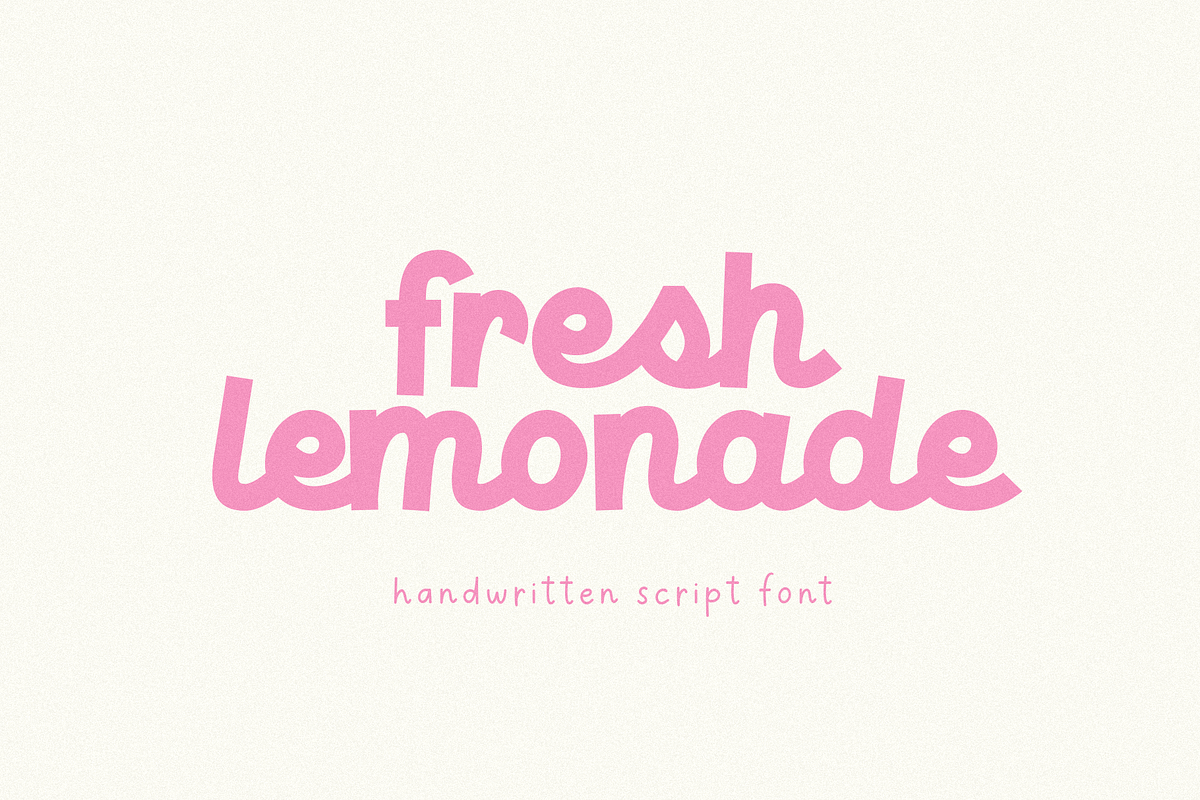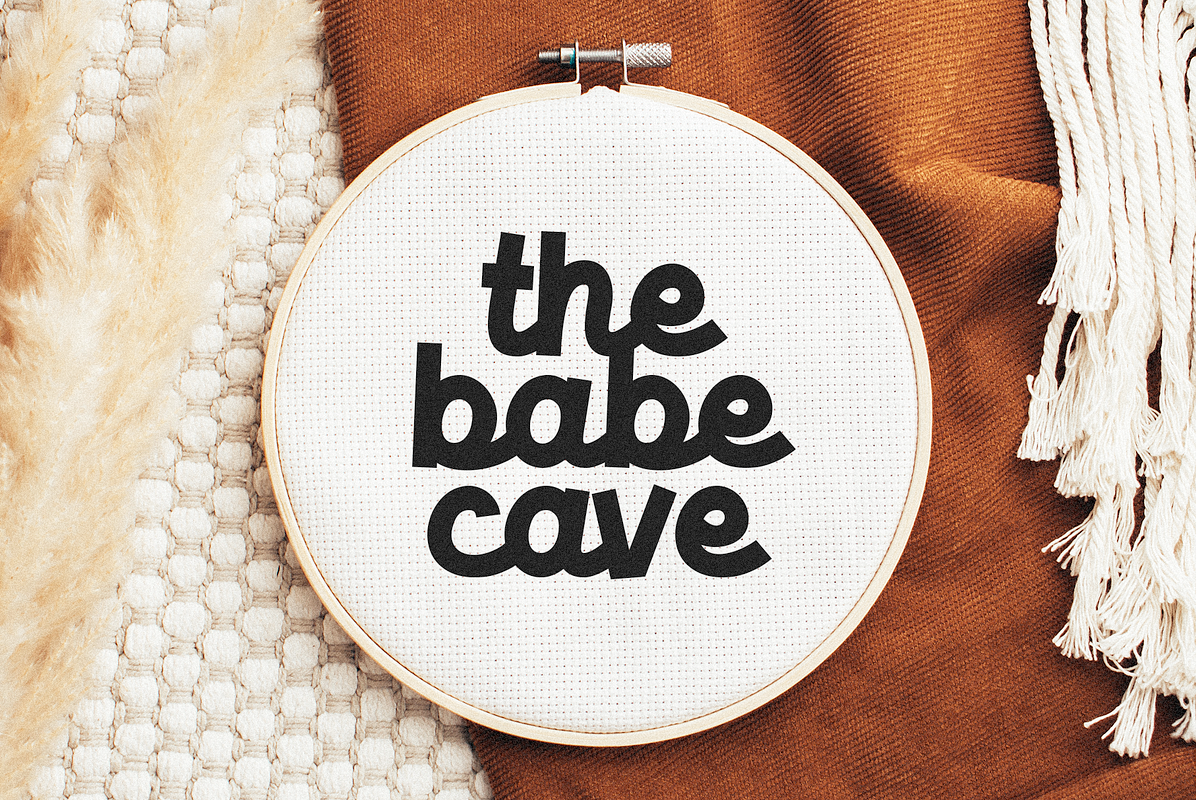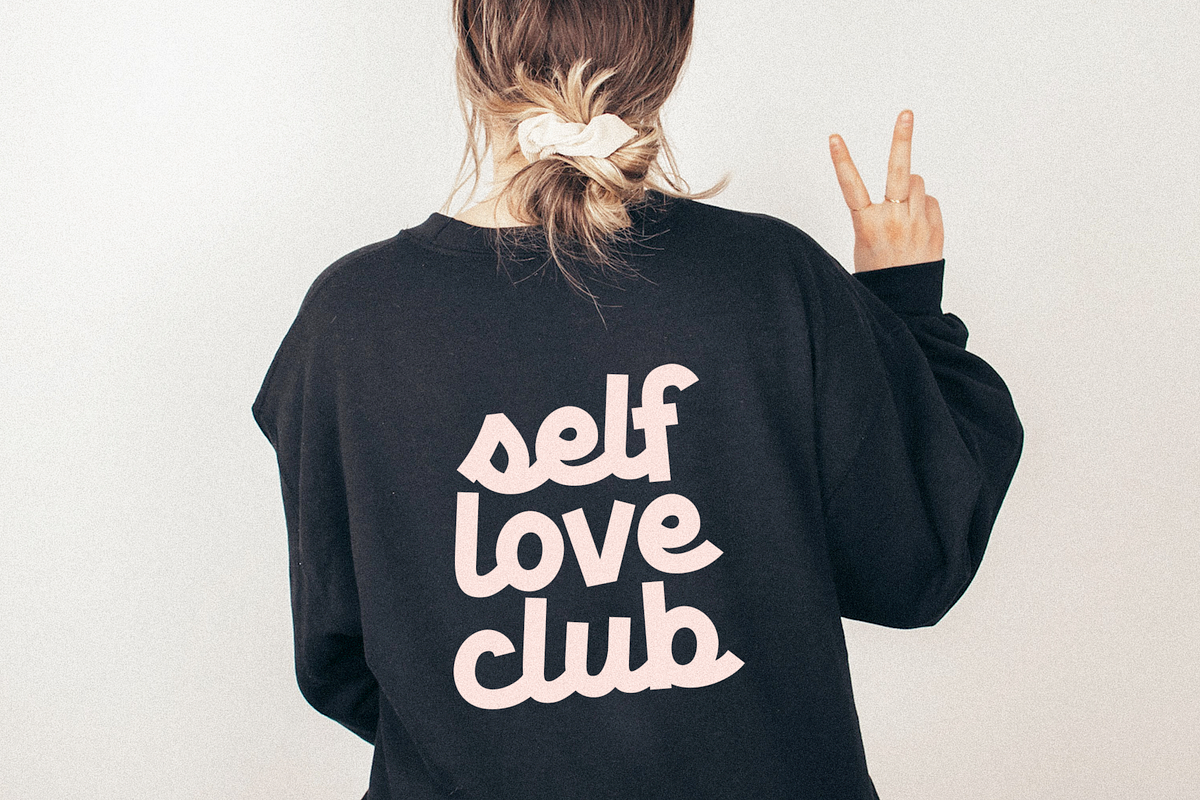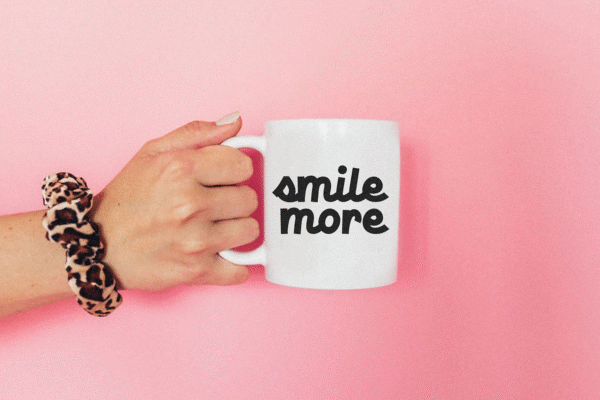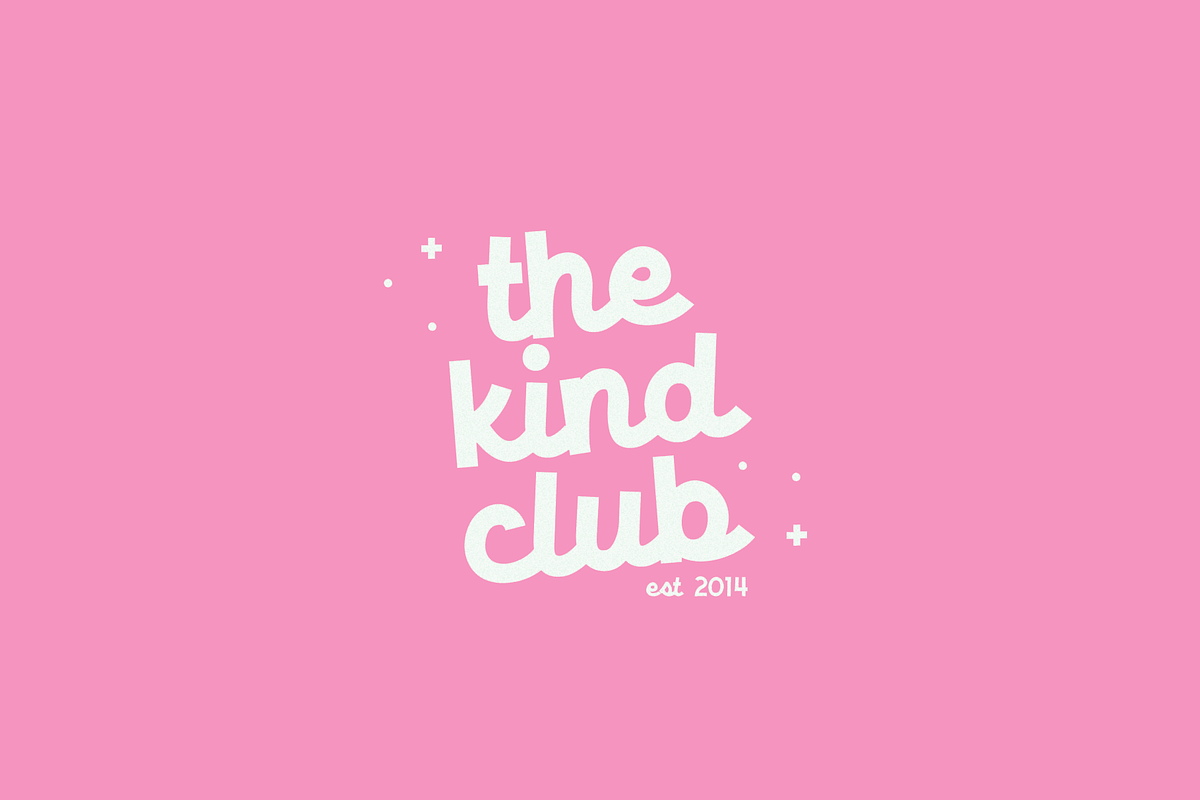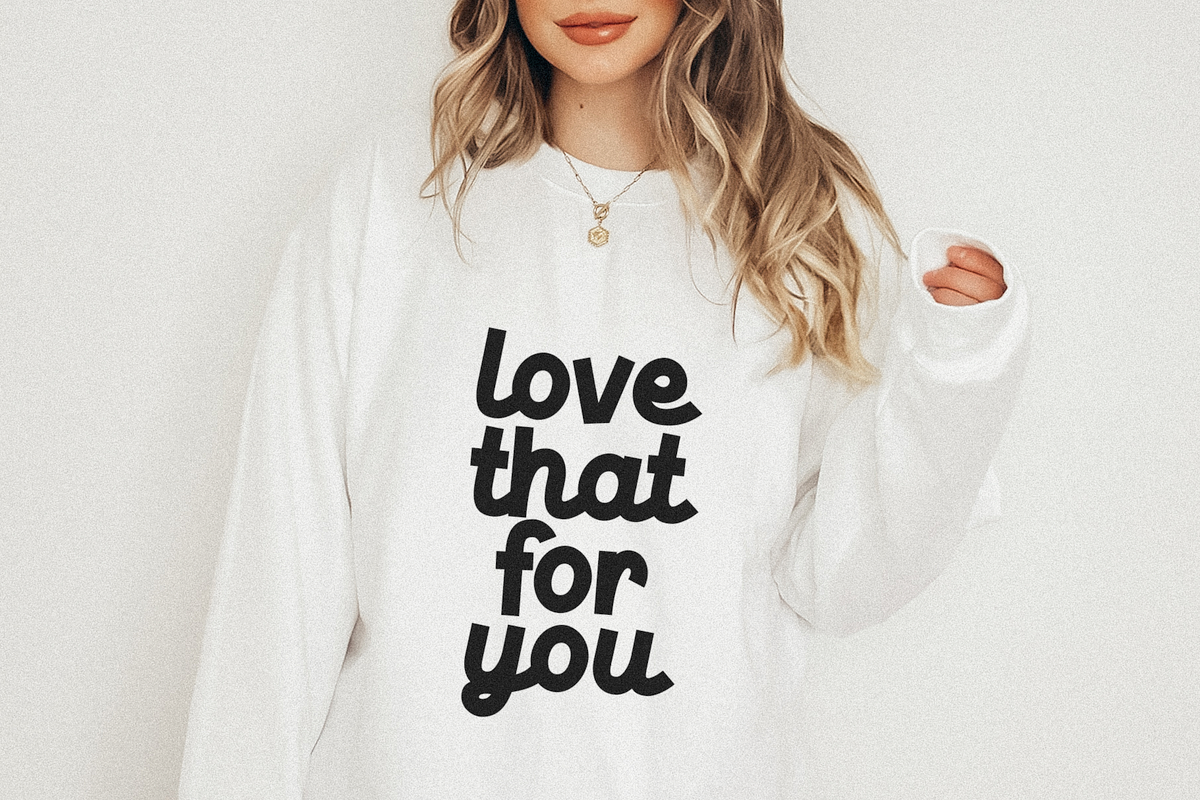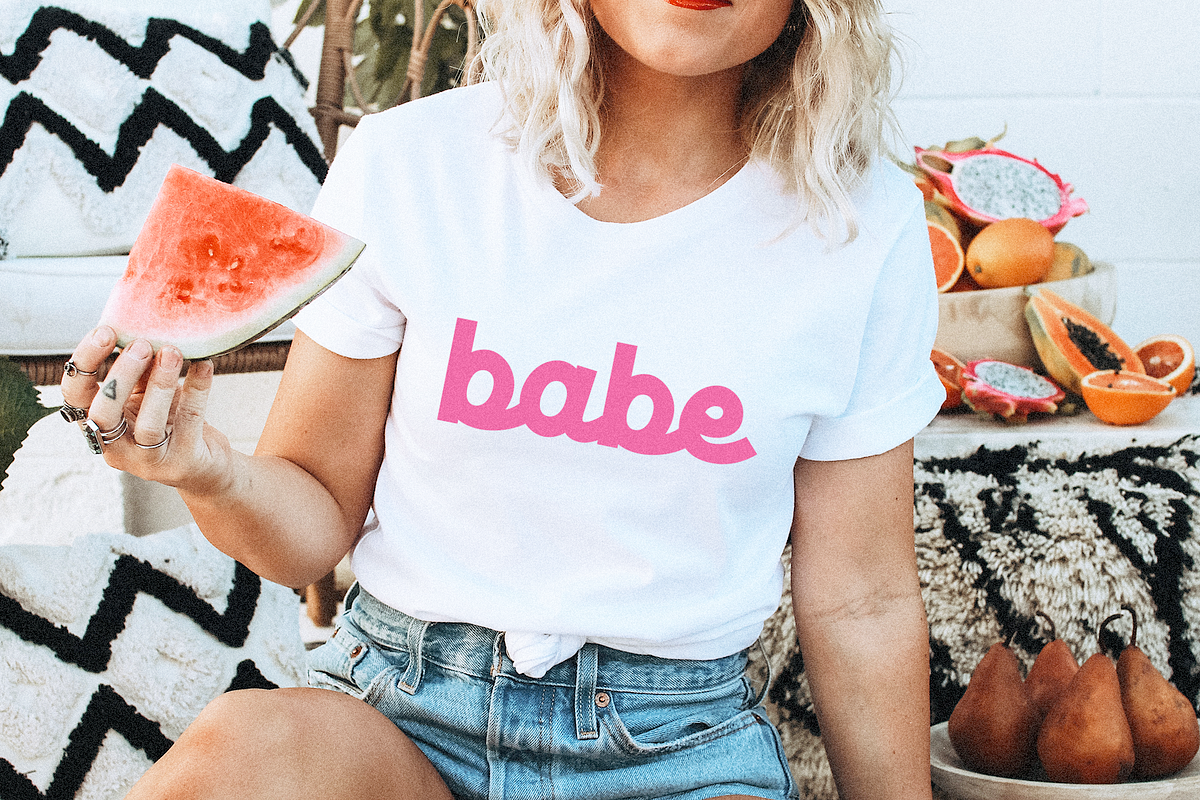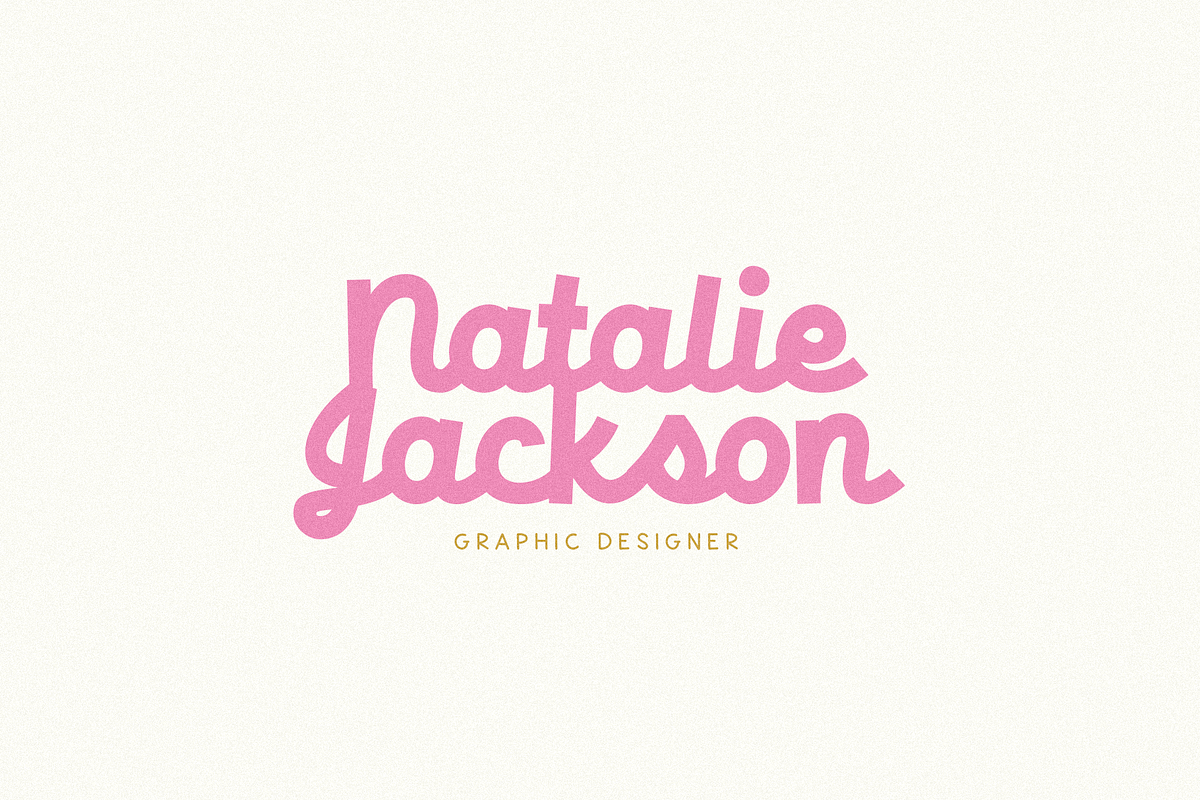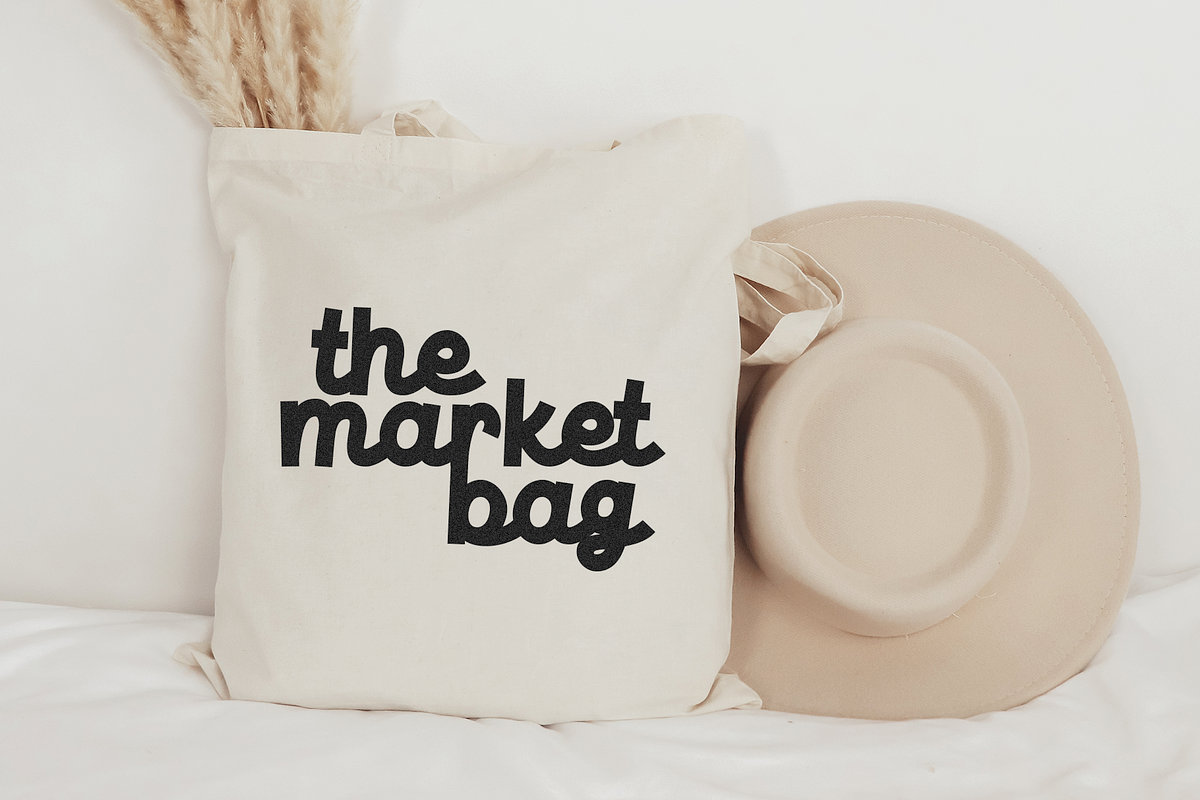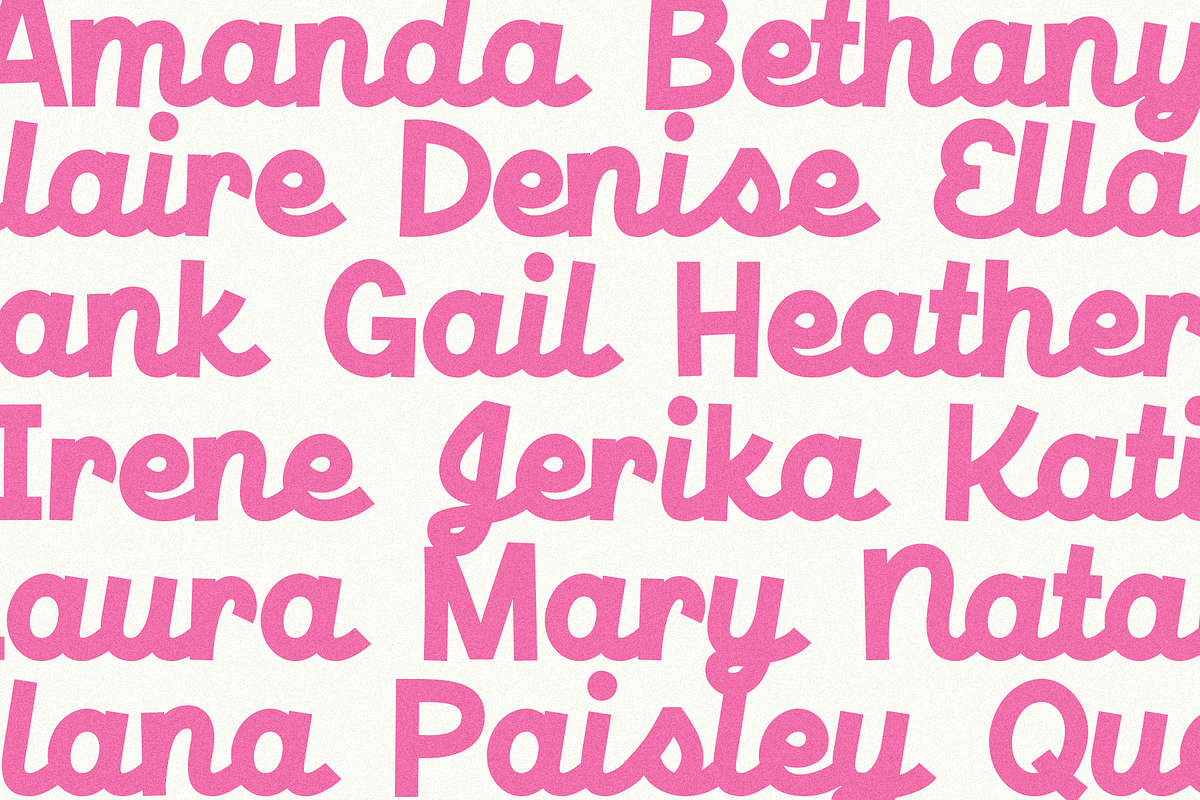
Fresh Lemonade | Script Font
Fresh Lemonade – Font Script Tulisan Tangan Bergaya Retro
Fresh Lemonade adalah font script dengan gaya tulisan tangan yang segar dan penuh karakter. Cocok digunakan untuk berbagai proyek kreatif seperti desain retro, file SVG, kaos, stiker, logo, konten media sosial, dan banyak lagi!